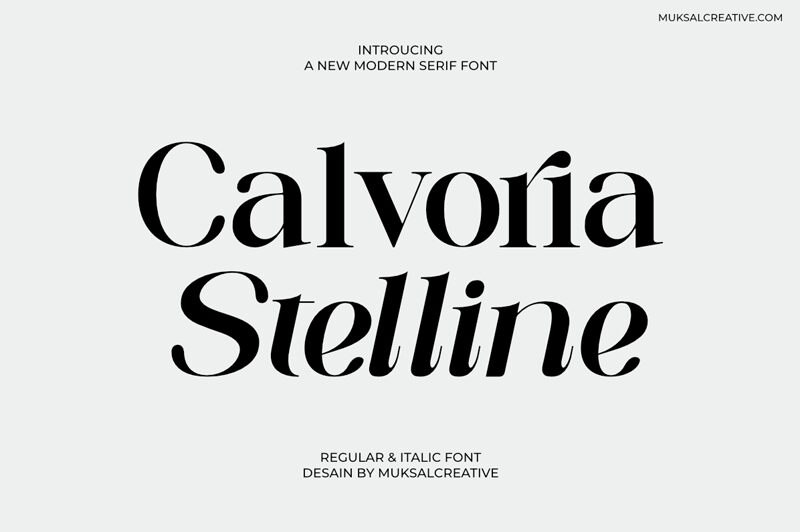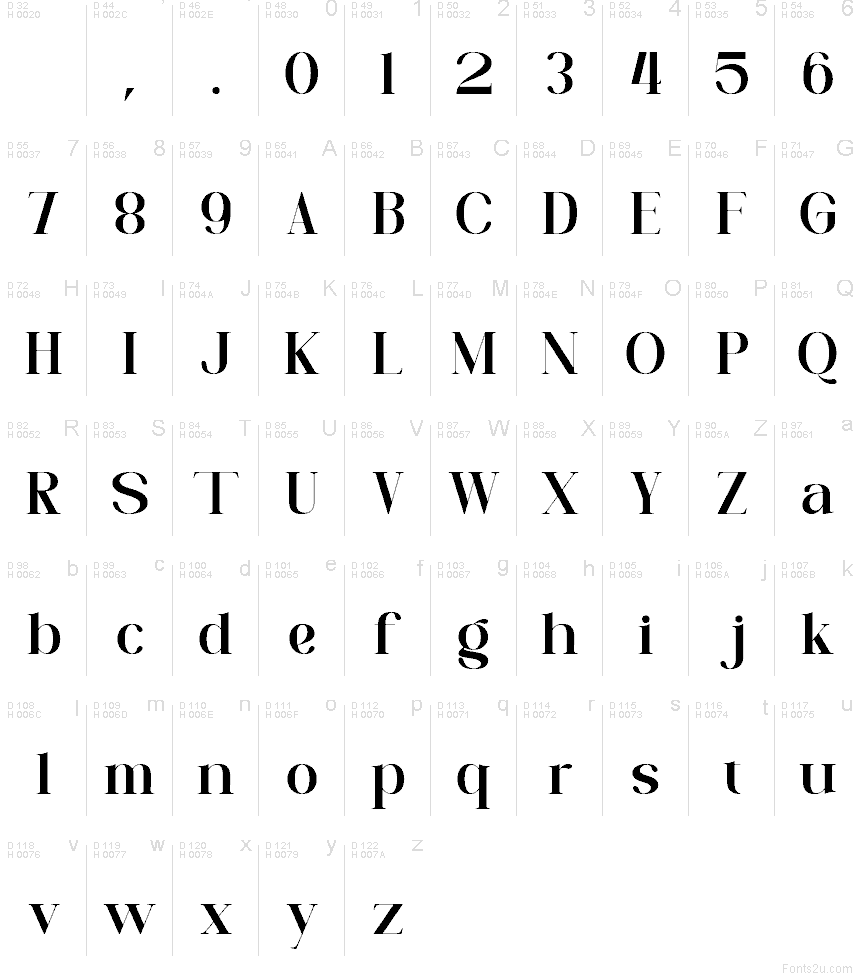
Calvoria Stelline Regular
Calvoria Stelline هو خط ذو زوائد (serif) عالي التباين من تصميم Muksal Creative، يتميز بمنحنيات عريضة ووصلات دقيقة للغاية، مما يمنحه مظهراً أنيقاً وعصرياً. تكمن حيوية الخط في التباين بين الأشكال المستديرة الممتلئة والأطراف الحادة، مما يضفي على الحروف خفة هوائية مع الحفاظ على طابع درامي ومنحوت.
هذا المزيج يجعله مثالياً لتغليف مستحضرات التجميل، عناوين المجلات، العلامات التجارية الفاخرة، بطاقات الدعوات، وعناوين منصات التواصل الاجتماعي. بينما قد تختفي الخطوط التقليدية، يبرز Calvoria Stelline بتبايناته وانسيابيته ليؤطر الأسماء والشعارات والعناوين بحضور تحريري مميز.